抖音短视频是目前受年轻人喜爱的一款短视频工具,每一款短视频画面上都附带有好多好看的字体呢,字体是从何处来的呢?哪里可以得到这么多好看的字体呢?同学们现在“字体视界”他来了。
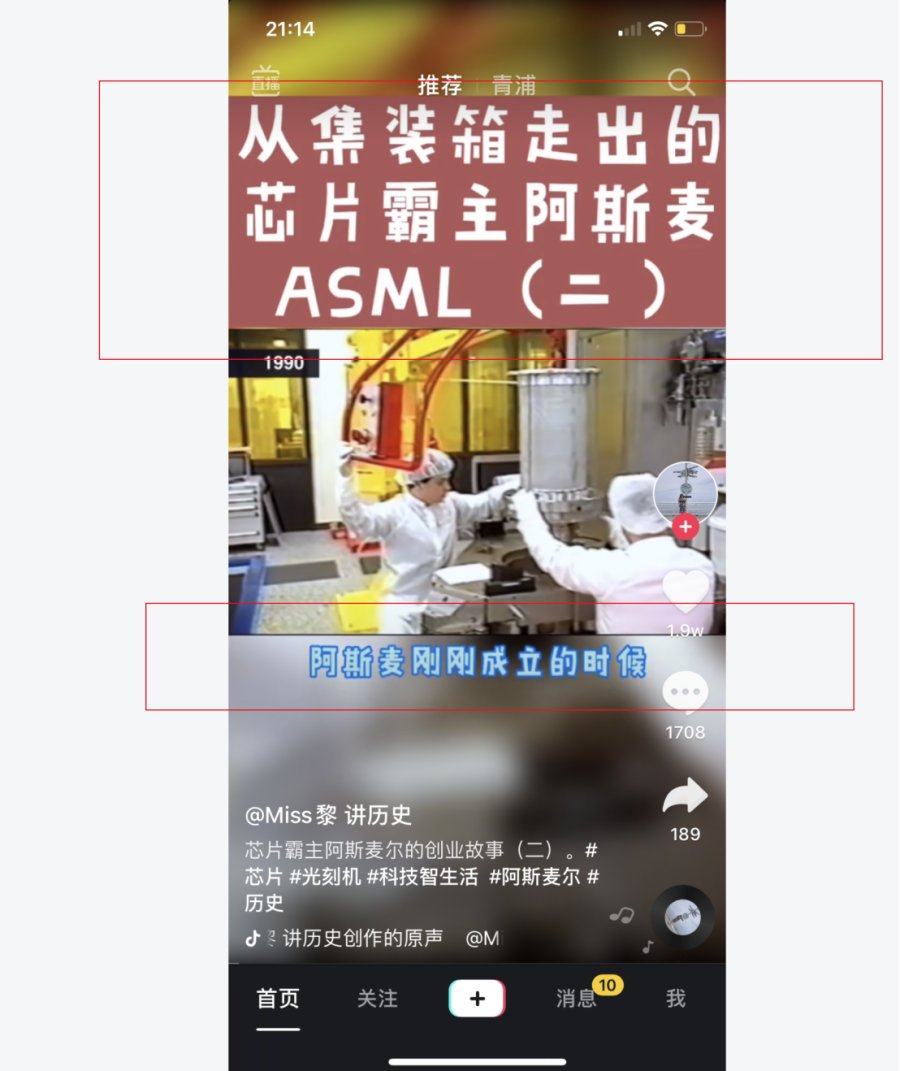
字体视界作为国内知名字库授权网站,字体种类众多,每一款字体都很适合短视频画面字体整体方正。关于字体正版问题,每位短视频的小主门都可以放心,字体视界提供的都是正版字体,您可以放心使用“字体视界”下载的每一款字体(小编提示“商用需授权后在使用哦,可以直接点击网站上客服联系授权”)。除了黑体、宋体、圆体等标准字体,海有很多手写体、创意体、卡通字体、图片字体都很适合抖音等短视频平台。
正统字体并不是什么新鲜事物,但是他的方正得体是不可缺少的,但是这些年来他已经开始流行创意字体,手写字体,从各短视频、社交媒体、海报你都能看到创意字体与手写体的身影他们都方正大方。下面小编为您整理了几款字体视界上深受短视频喜欢的字体。
汉标高清锐毛【抖音网红字体推荐一】
汉标智造国楷【抖音网红字体推荐二】
骑上我の小摩托【抖音网红字体推荐三】
青春的天空